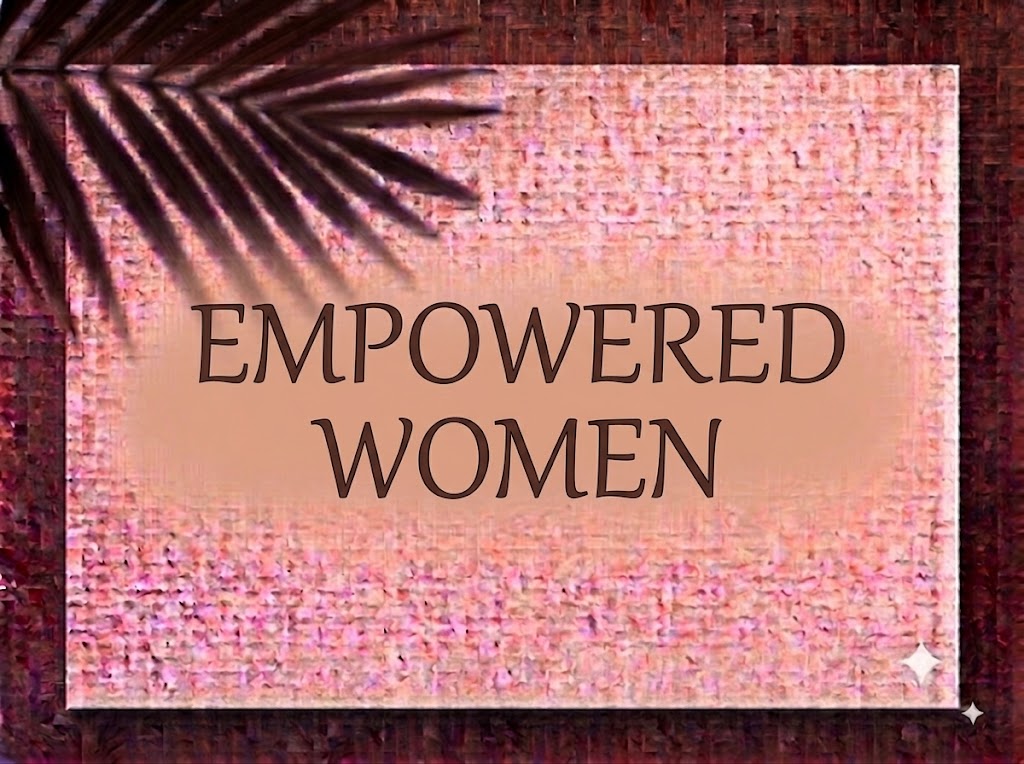
1FTV Ballein
Trong nghệ thuật thiết kế đồ họa cao cấp và xuất bản tạp chí (Editorial), việc sở hữu một bộ phông chữ hiển thị (display font) vừa mang cấu trúc thanh mảnh kiêu sa, vừa sở hữu những đường nét uốn vát phá cách luôn là điểm nhấn đắt giá. Một dòng tiêu đề tinh tế không chỉ giúp tác phẩm trở nên trang nhã, giàu chất thơ mà còn tôn vinh đẳng cấp thương hiệu.
Nếu bạn đang tìm kiếm một phông chữ Serif thanh thoát, đậm chất nghệ thuật để làm bìa lookbook, nhận diện thương hiệu spa, mỹ phẩm, thời trang thiết kế hay tiêu đề video ngắn, font 1FTV Ballein chính là sự lựa chọn không thể bỏ qua.
Giới thiệu về font 1FTV Ballein
Font 1FTV Ballein là bộ chữ hiển thị có chân (display serif) mang phong cách tân cổ điển thanh lịch, nổi bật với sự kết hợp hài hòa giữa nét chữ thanh mảnh và những nét biến điệu uốn cong tinh xảo:
Tên phông chữ: 1FTV Ballein
Được thiết kế và hoàn thiện kỹ lưỡng trên chuẩn OpenType, phông chữ đem lại khả năng hiển thị vô cùng sắc nét. Bạn có thể tự tin phóng lớn tiêu đề trên các ứng dụng đồ họa chuyên nghiệp hay phần mềm dựng video mà không lo bị vỡ nét hay răng cưa.
Đặc điểm nổi bật của phong cách thiết kế Ballein
Sức hút thị giác của font 1FTV Ballein đến từ phom dáng thanh thoát cùng những đường nét uốn vát đầy tính mỹ thuật:
Nét thanh đậm tương phản tinh tế: Cột nét dọc đứng dáng kết hợp cùng các đường nét ngang, nét cong mỏng nhẹ tạo nên cảm giác nhẹ nhàng, bay bổng và đầy chất nghệ thuật.
Chi tiết biến điệu đuôi & nét cong độc đáo: Điểm nhấn đắt giá nằm ở các nét cong vòm mềm mại, đuôi chữ uốn nhẹ ở các ký tự như
T,h,e,q,u,k,b,r,f,x,j,m,p,s… Chi tiết này gợi liên tưởng đến nét bút lông thư pháp phương Tây được hiện đại hóa. -
Đồng bộ trọn bộ chữ hoa và chữ thường: Dàn chữ cái in hoa trang nhã kết hợp hoàn hảo cùng bộ chữ thường kiều diễm và dãy số 0-9 dáng đứng thanh lịch, giúp các designer dễ dàng tạo nên những layout cân đối và có chiều sâu.
Khoảng cách giữa các chữ (kerning) và độ giãn dòng được tính toán chuẩn xác, giúp các nét cong uốn lượn khi đứng sát nhau không bị dính nét hay rối mắt.
Tích hợp trọn vẹn bộ chữ cái hoa – thường, dãy chữ số 0-9 phom dáng nghệ thuật cùng hệ thống ký tự đặc biệt, dấu câu thông dụng.
Bản Việt hóa chuẩn chỉnh giúp bạn hoàn toàn yên tâm thiết kế các văn bản tiếng Việt có dấu phức tạp mà không gặp lỗi nhảy font hay mất ký tự.
Hình ảnh demo thực tế của font 1FTV Ballein
Khả năng hiển thị của phông chữ này được tối ưu rất tốt trên nhiều tỷ lệ kích thước khác nhau:
Kích thước nhỏ (12pt – 24pt): Cấu trúc chữ thanh mảnh và khoảng hở nội tại thoáng giúp các câu chữ và dãy số vẫn hiển thị rõ ràng trên màn hình di động.
Kích thước lớn (36pt – 72pt): Đây là đất diễn hoàn hảo nhất để 1FTV Ballein phô diễn toàn bộ sự kiêu sa, đài các của các đường uốn nét nghệ thuật, tạo tác động thị giác mạnh mẽ cho các dòng headline chính.
Ứng dụng trong thiết kế đồ họa và làm video
Sở hữu nét cá tính thanh lịch và giàu tính thẩm mỹ, font 1FTV Ballein mở ra không gian ứng dụng phong phú:
Video ngắn (TikTok, Reels, Shorts): Dáng chữ Serif thanh lịch hiển thị rất thu hút trên khung hình đứng tỷ lệ 9:16. Cực kỳ ăn nhập với các video vlog thời trang, review mỹ phẩm, trang sức, spa, phong cách sống hay clip nghệ thuật.
Ảnh thu nhỏ YouTube (Thumbnail): Lựa chọn tuyệt vời cho các kênh làm nội dung về làm đẹp, thời trang, âm nhạc Acoustic, Lofi Chill hoặc podcast nhờ diện mạo sang trọng và thanh nhã.
Thiết kế Bìa Tạp chí, Lookbook và Poster: Hoàn hảo cho các sản phẩm truyền thông thuộc lĩnh vực thời trang thiết kế, spa chăm sóc da, triển lãm nghệ thuật, bìa tiểu thuyết hay thiệp cưới cao cấp.
Nhận diện thương hiệu phân khúc Luxury: Thích hợp làm logo dạng chữ, bao bì mỹ phẩm organic, nhãn mác nến thơm, nước hoa hay menu nhà hàng/khách sạn cao cấp.